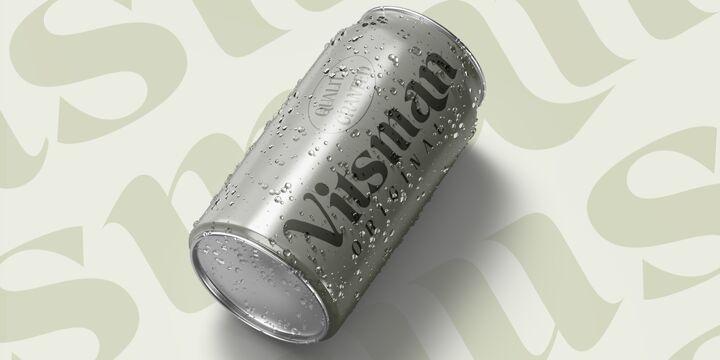
Railing Font
Description de Railing Font
Êtes-vous à la recherche d’une police d’affichage ? Vous rêvez de créer des titres qui se démarquent et inspirent la créativité, l’imagination et un plaisir sans fin ? N’attendez plus, nous vous proposerons le meilleur choix. Railing est une police magnifique, conçue avec une ambiance moderne. Cette police est parfaite pour tout ce qui est simple et direct. Chaque trait et chaque courbe ont été créés pour attirer le bonheur et l’élégance. Un véritable accroche-regard pour votre présentation, vos designs, votre image de marque, vos citations, vos invitations, vos illustrations de sites Web et bien plus encore.